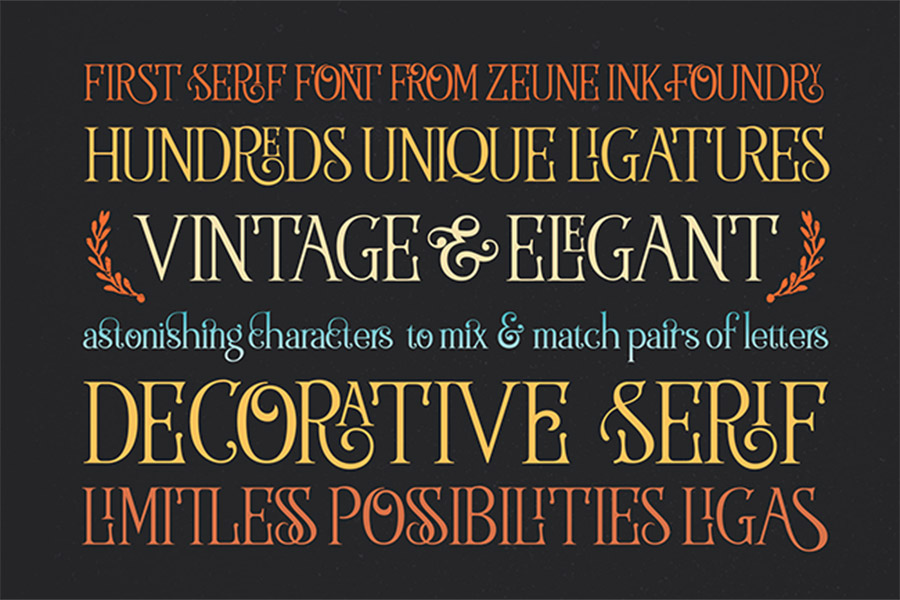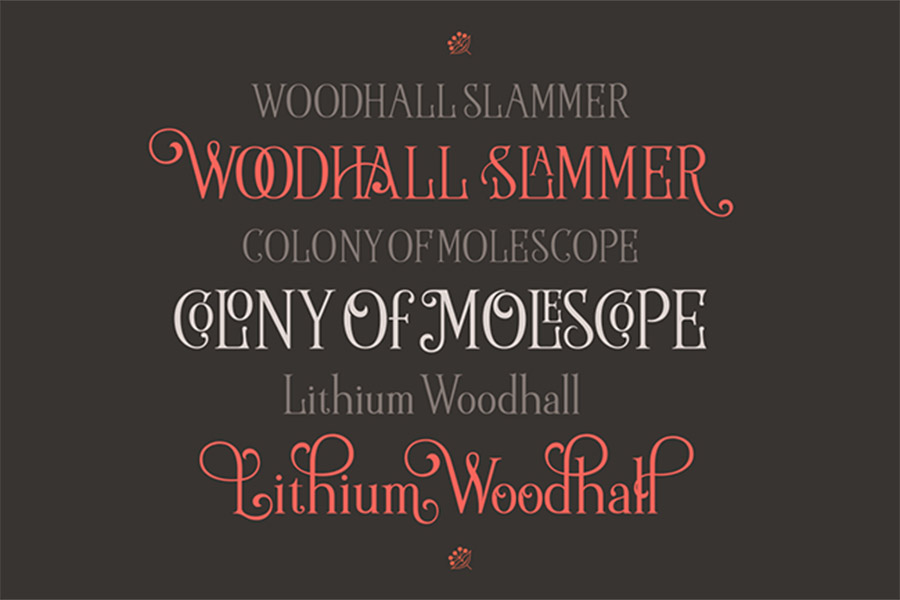
Wallington là một font chữ tải cho Photoshop giúp bạn viết tiếng Việt mà không lỗi font. Đây là font chữ nhẹ nhàng, bay bổng phù hợp với nhiều văn bản được thiết kế theo nhiều phong cách.